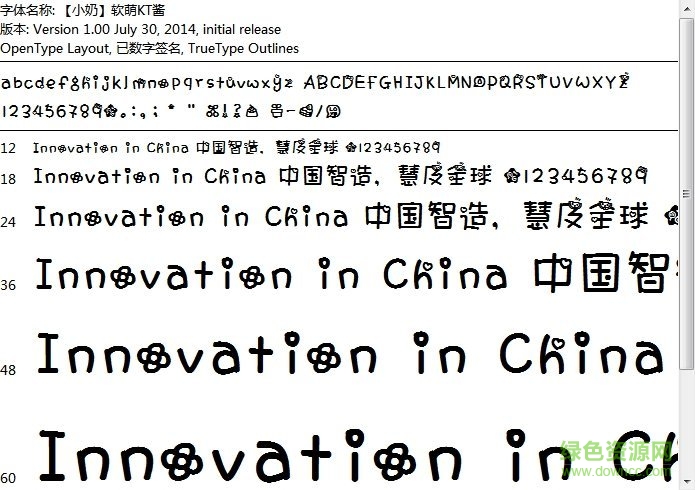
Aa软萌小姐姐字体是字体管家上的一款非常软软萌萌的卡通字体,有着心形和花型的点缀修饰,让文字也有了自己的个性和温暖色彩,给大家更多的想象空间,快来绿色资源网试试吧!
软萌小姐姐字体字库完整不缺字,支持中英文和繁简体书法,用于非主流设计方面的字体,同样适用于广告设计字体、网页设计字体、包装设计字体、 屏幕显示字体等。
超级可爱的二次元少女字体,各种表情加上可爱的装扮,对于女生来说这款天然萌字体绝对的杀伤力巨大!